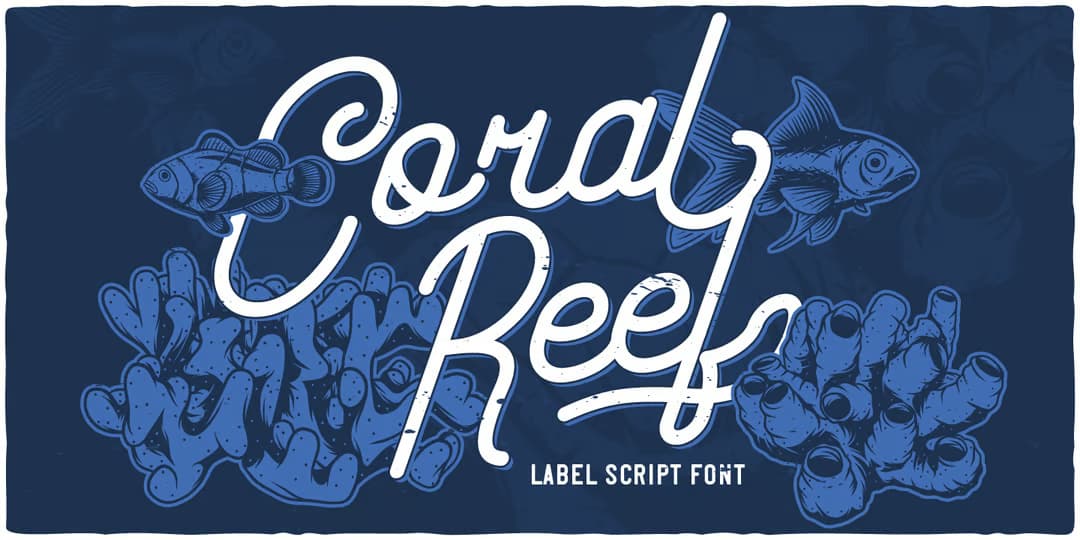
本日『サンゴの日』だそうなのでこちら。モノラインのやや幾何学的なスクリプト。あんまり手書きっぽくないタイプで、ボウル部分がグラウンド型長楕円がベースになっており、それに合わせて他のストロークも結構かっちりしているが、雰囲気はあくまでレトロカジュアルで柔らかい。ちょっとしたスワッシュ付きのオルタネートもあり。1ウェイト。